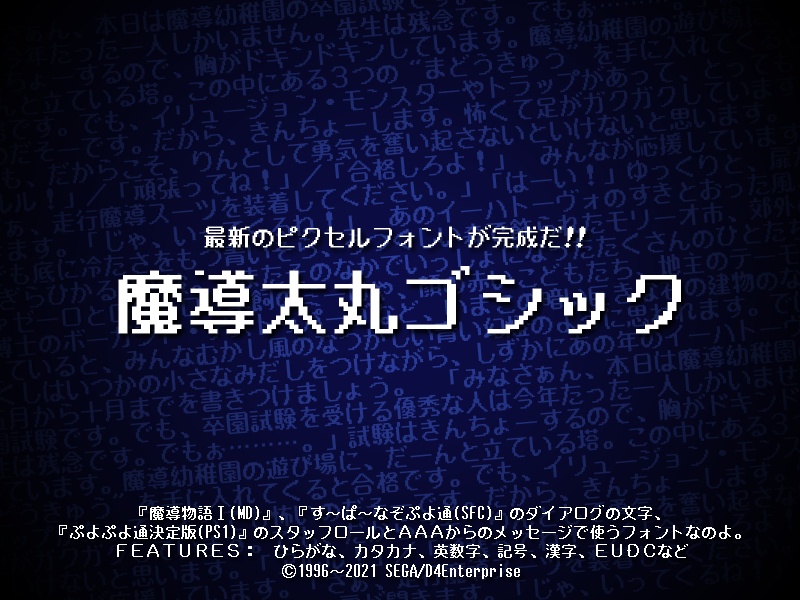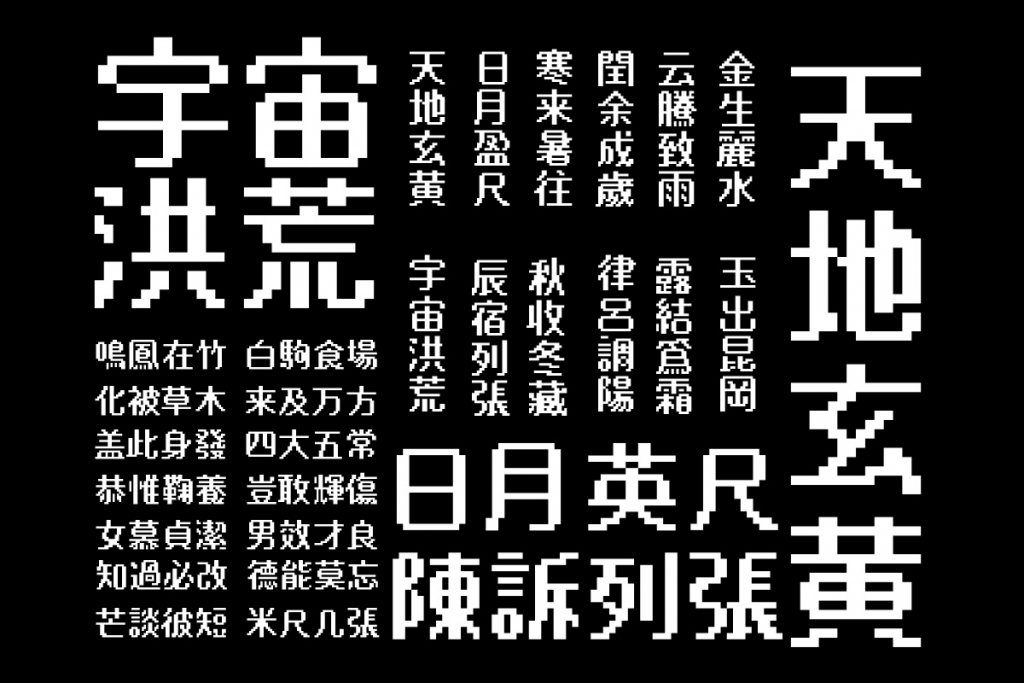
魔道哥特像素体字体信息
城里最新的像素字体!
魔導太丸ゴシック终于完成了!
你可以在《魔導物語Ⅰ(MD)》、《す~ぱ~なぞぷよ通(SFC)》(对话框文本),以及《ぷよぷよ通決定版(PS1)》的制作人员名单、结尾字幕和AAA消息中看到这个字体。
“魔道哥特像素体”是一款书写很新颖的字体,字体大方,适合各种设计作品使用!欢迎下载!